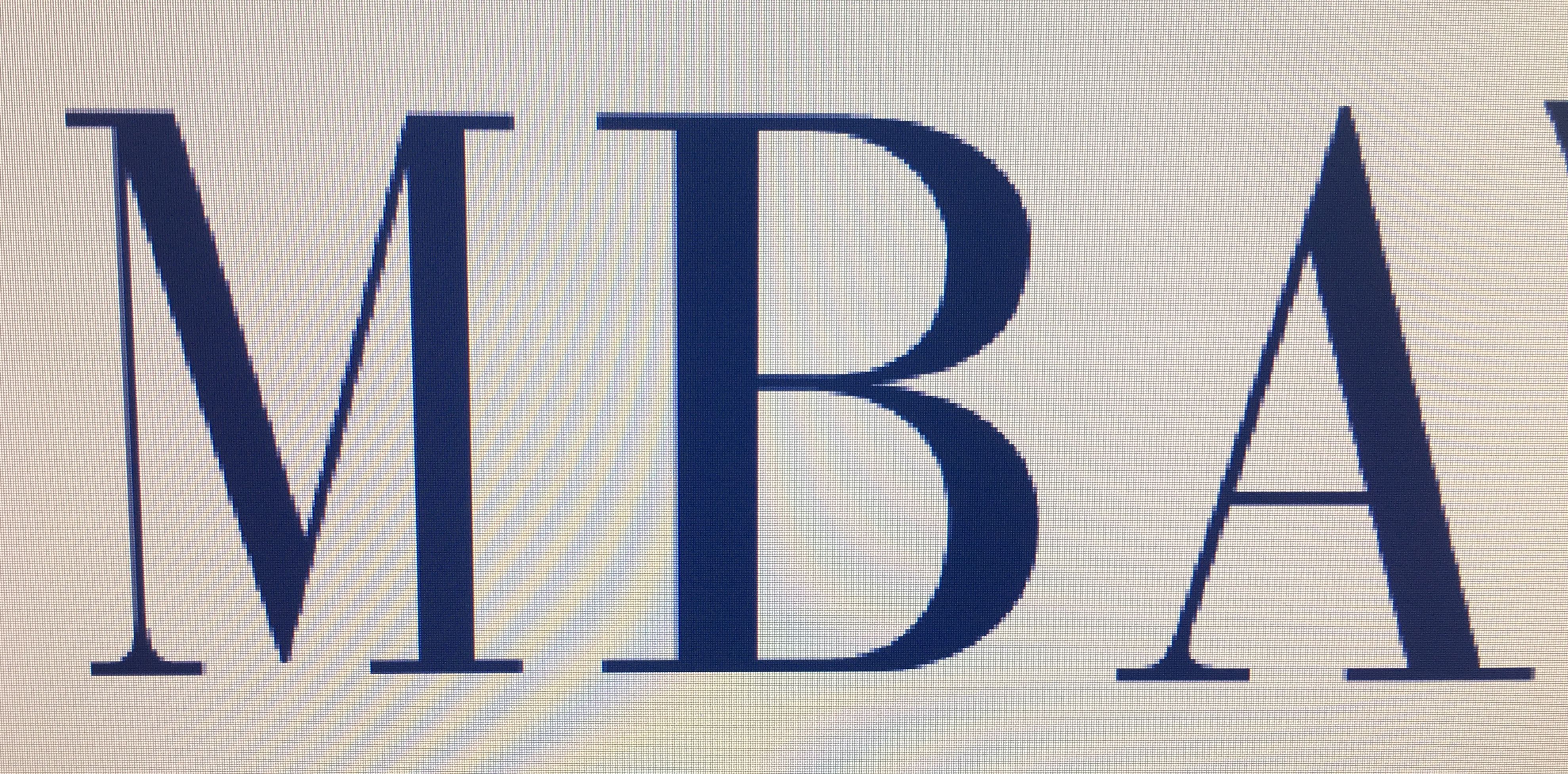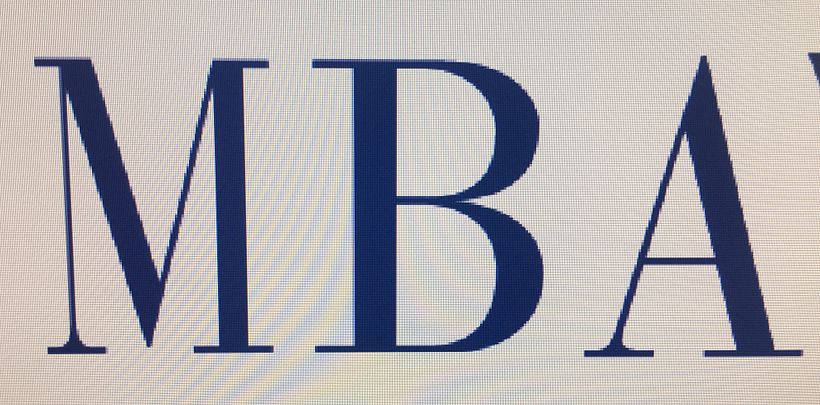
Si, se parece muchisimo a la Bodoni
Efectivamente es una foto distorsionada porque esta hecha a la pantalla del ordenador.
Y tan típica serif font, es la Bodoni @bohdanshila ^^'
No sé si la foto está distorsionada pero parece que sea la versión Pro Book de esta família @pbenito28.
¡Hola! Es una serifa bastante típica, seguro que puedes encontrar muchas que se le parecen. Por ejemplo esta: https://fonts.google.com/specimen/Playfair+Display